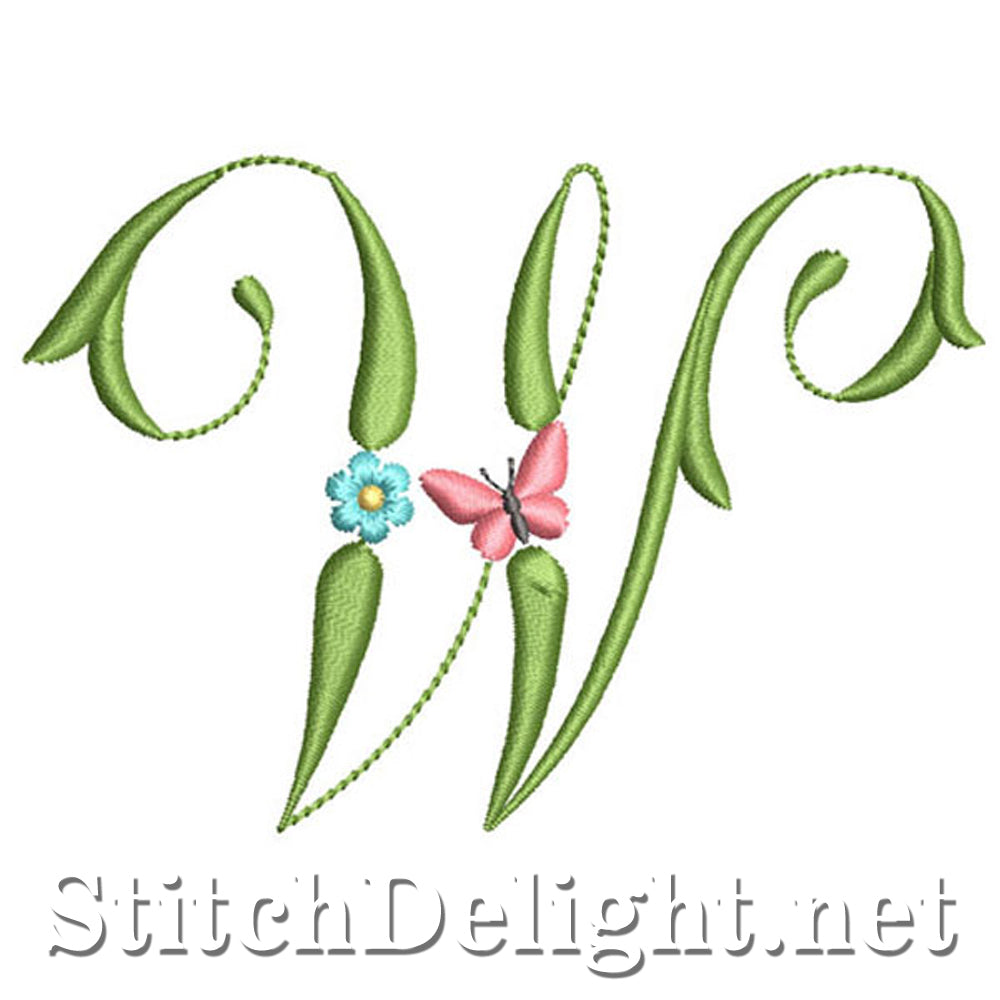
SDS1152 Schmetterlinge und Blumen Schriftart W
Schöne Schrift mit zierlichen Blumen und Schmetterlingen - Die Buchstabenhöhe dieser Buchstaben beträgt 67 mm / 2,65"